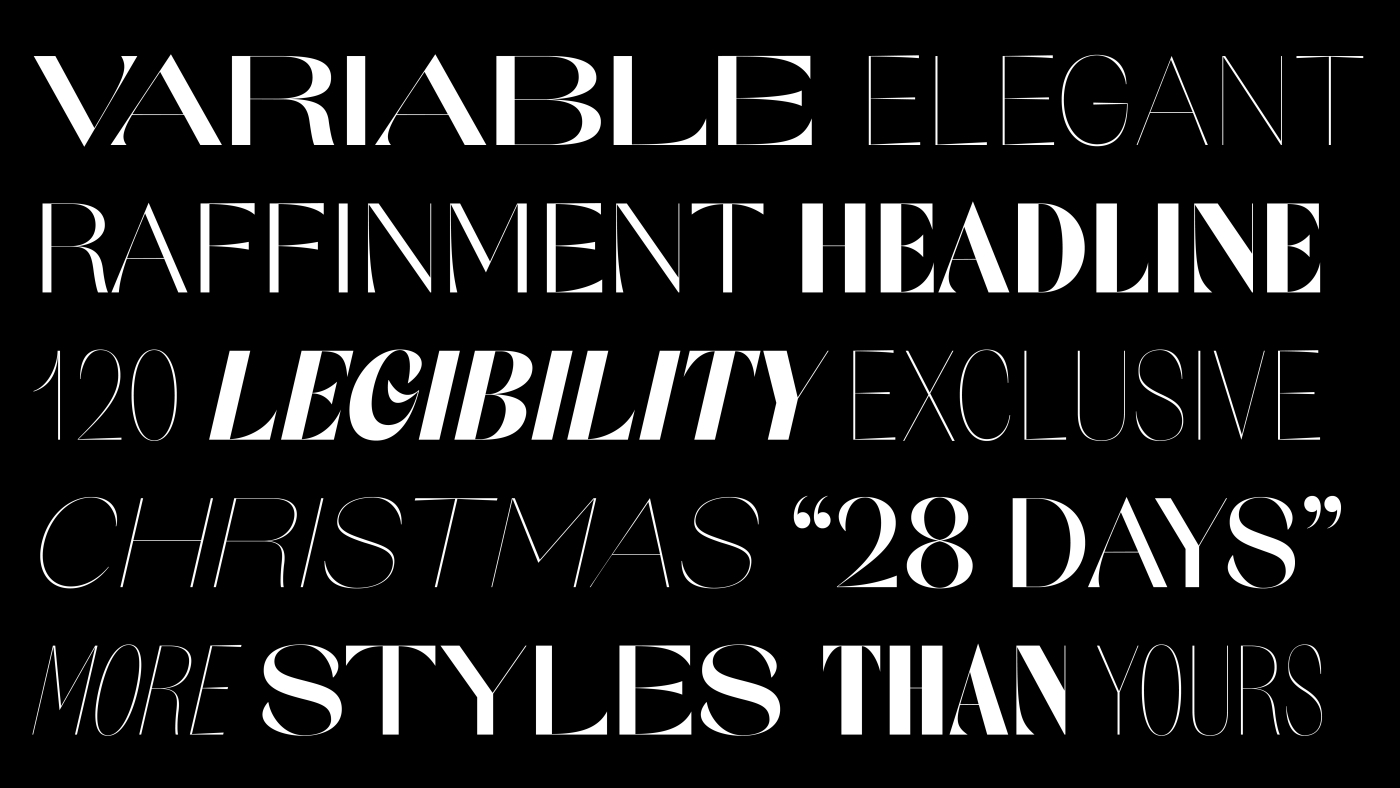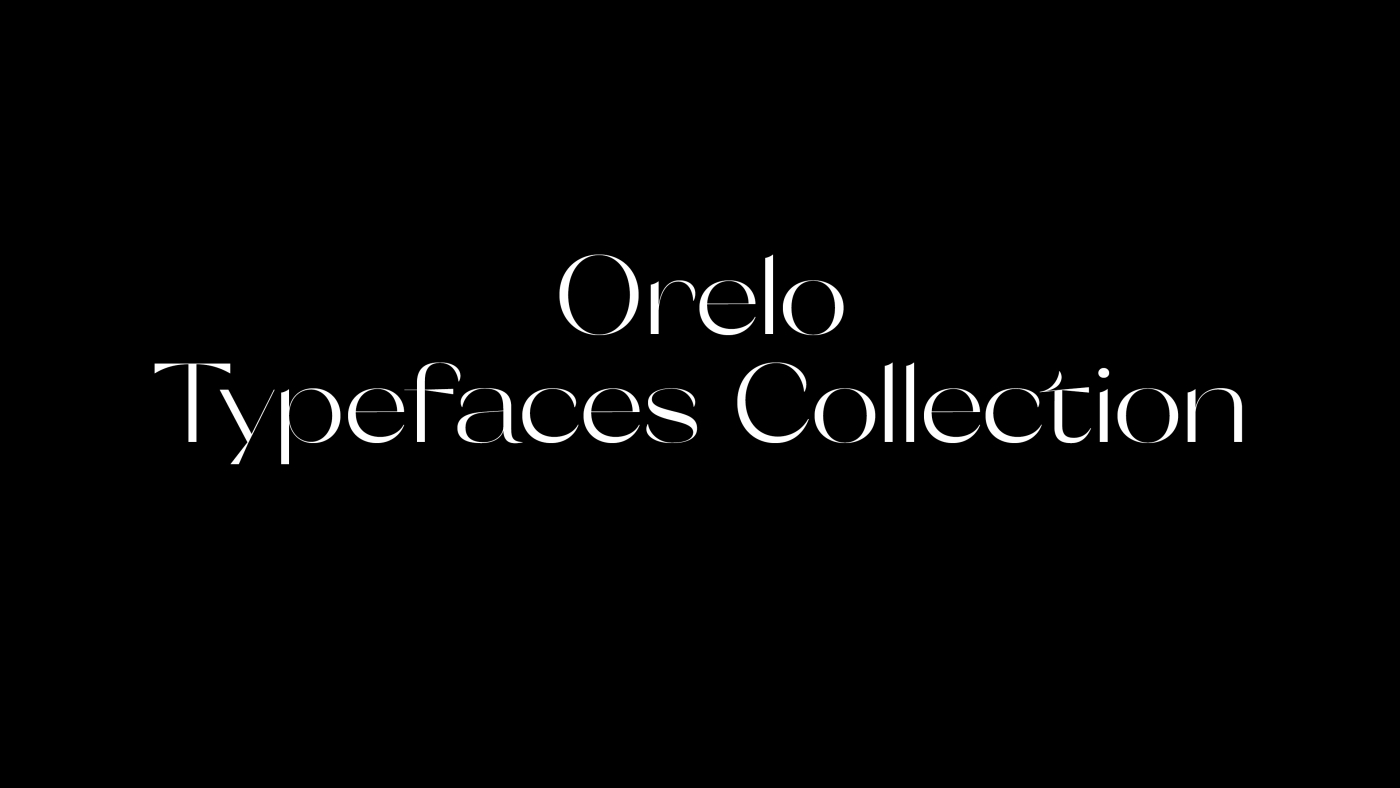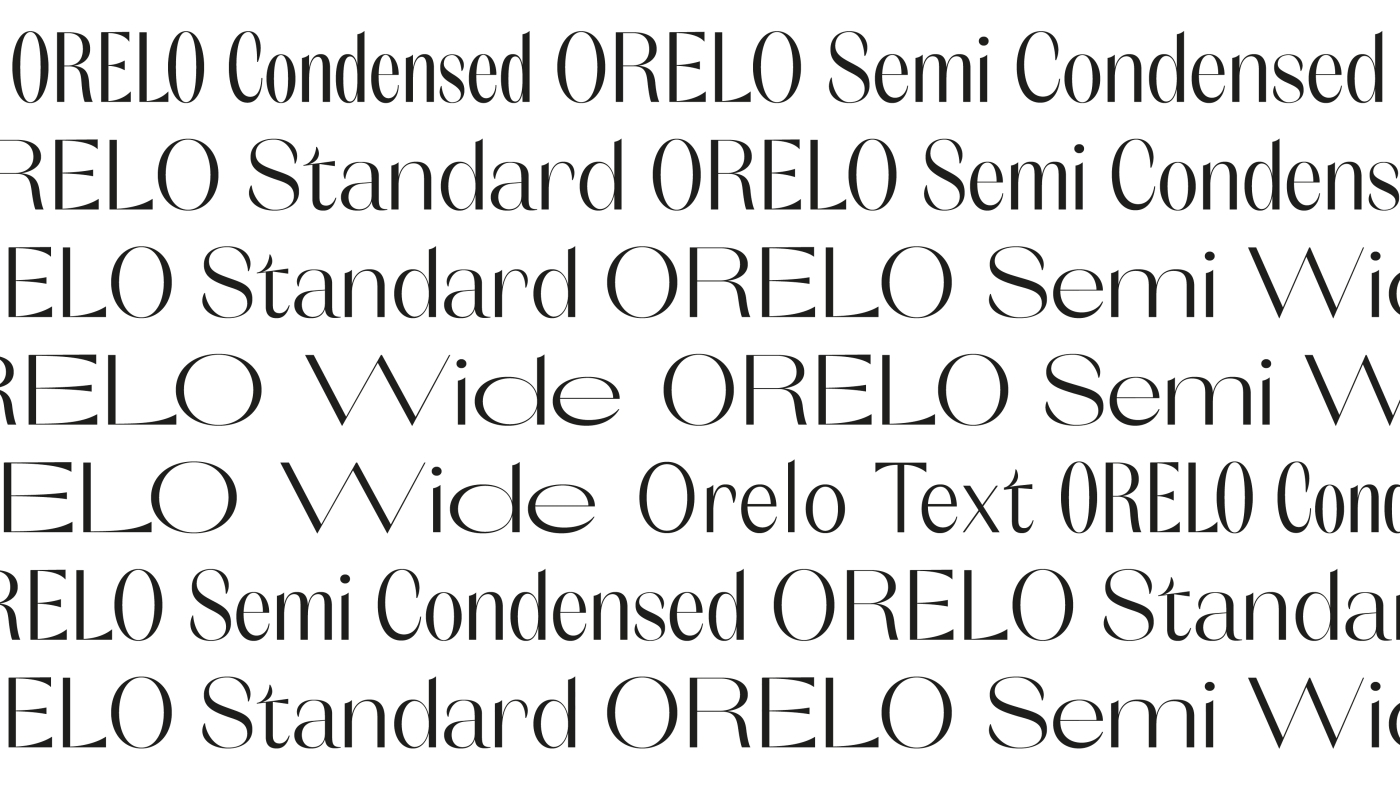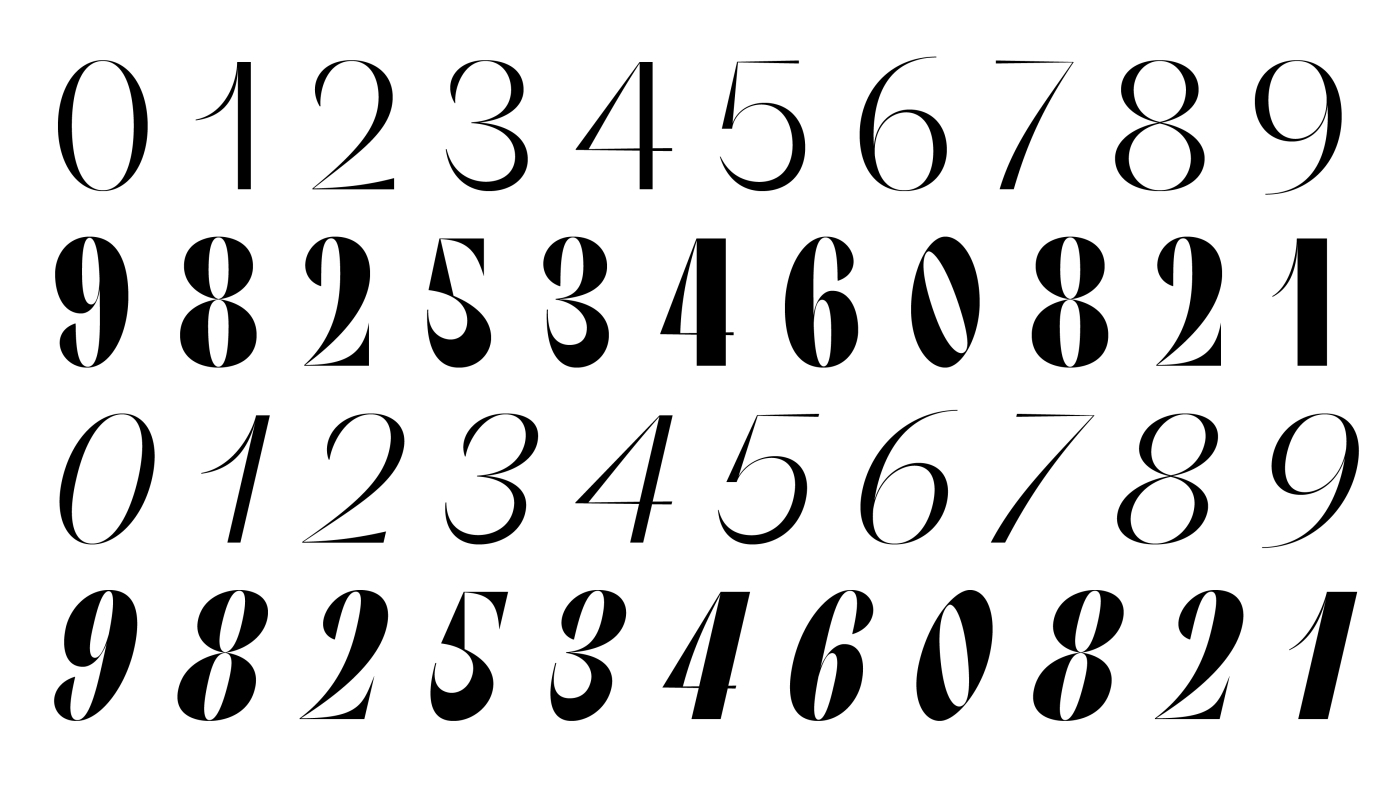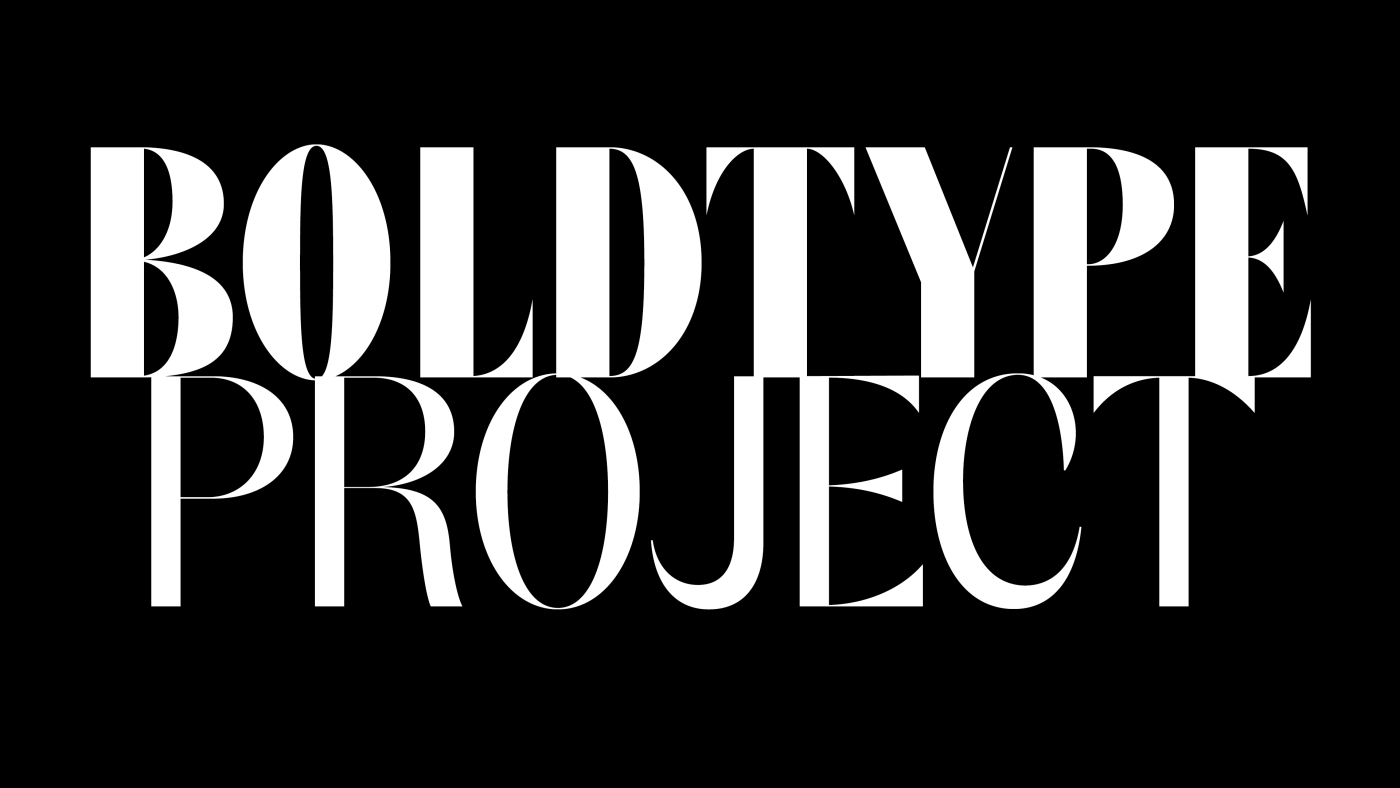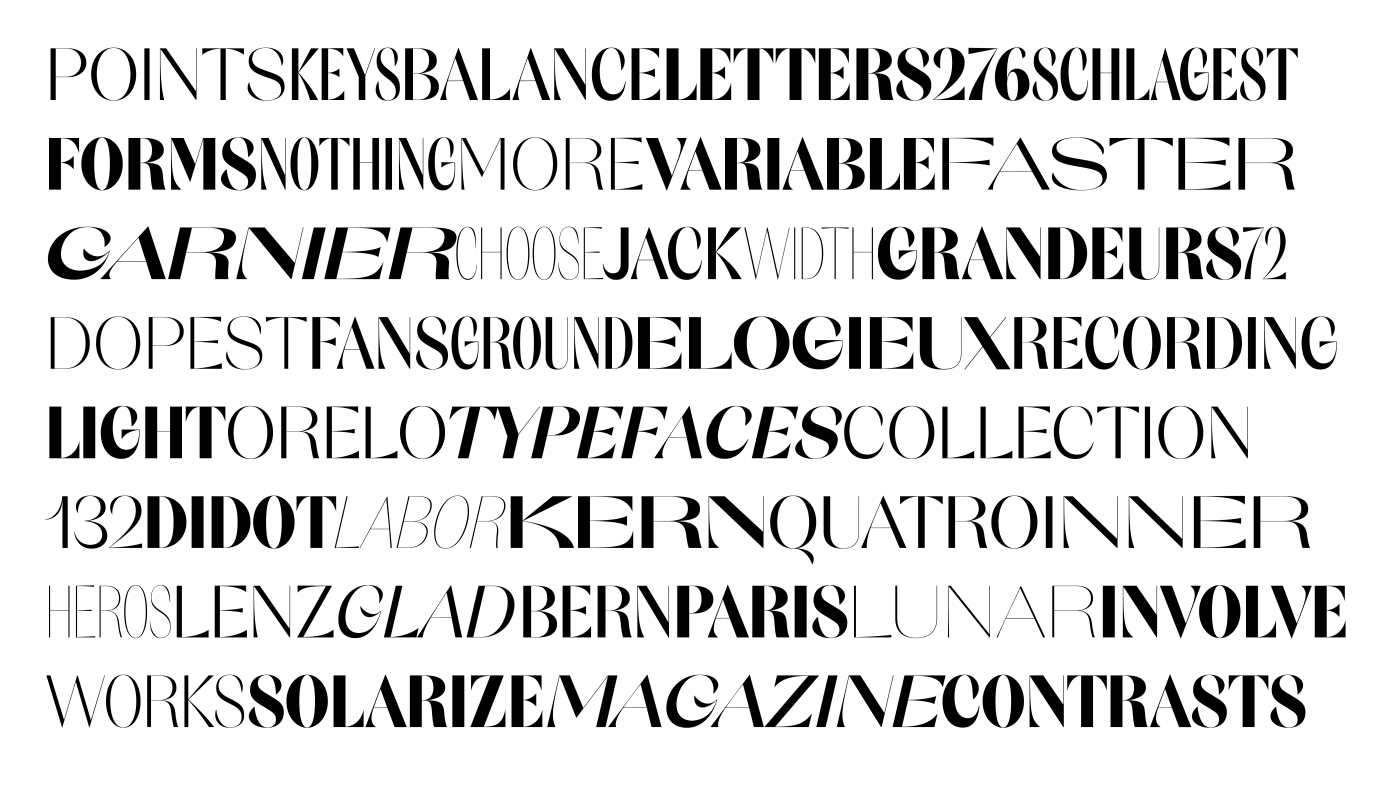
Orelo Typefaces Collection
Orelo est un projet initié dans le cadre de "Bold Type" (kickstarter/étapes: magazine).
C'est plus qu'une typographie, c'est une famille typographique développée en Variable-Font. Les variations se font sur 3 axes : largeur, graisses et italiques. Elle propose 120 styles, du Condensé Hair au Large Heavy avec leurs italiques respectifs ainsi qu'une version spéciale pour les textes longs. C'est une typographie inspirée des Didots françaises mais proposant une nouvelle approche de dessins. Équilibrée, contrastée aux formes contemporaine, Orelo est destinée aux titrages et textes courts.
Orelo Typefaces Collection permet aux utilisateurs exigeants de travailler avec plus que les styles prédéfinis d'une famille de polices standard. Vous pouvez profiter d'un éventail de quantités presque infinies de poids et de largeurs, se mélangeant en douceur du Condensé Hair au Large Heavy. Sélectionnez et utilisez n’importe quel style intermédiaire, un à la fois ou tous mélangés simultanément. Cette liberté offre de nouvelles possibilités créatives, que vous conceviez pour l'impression ou pour le Web.